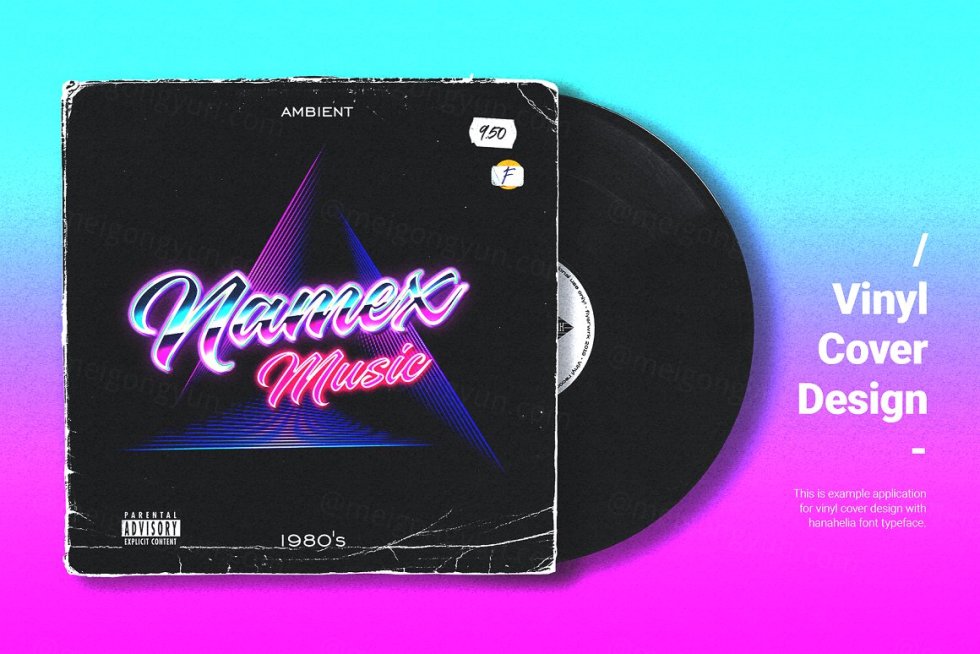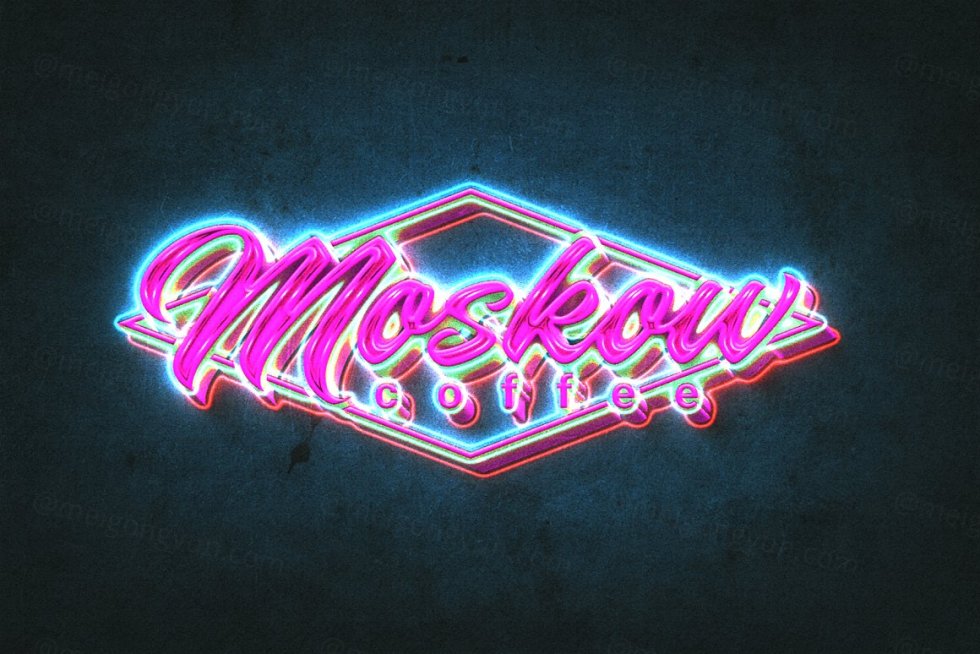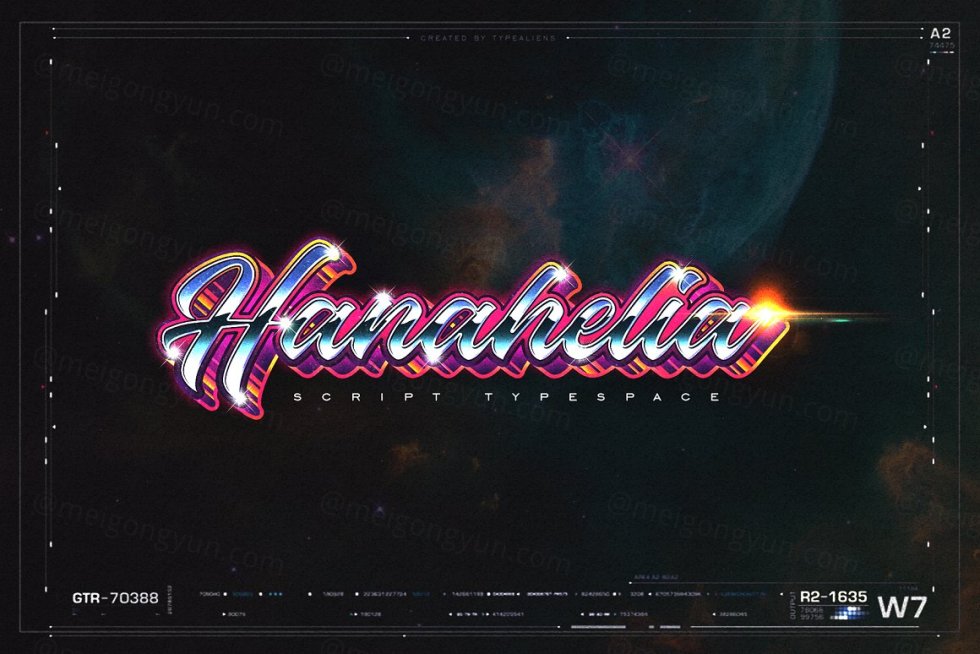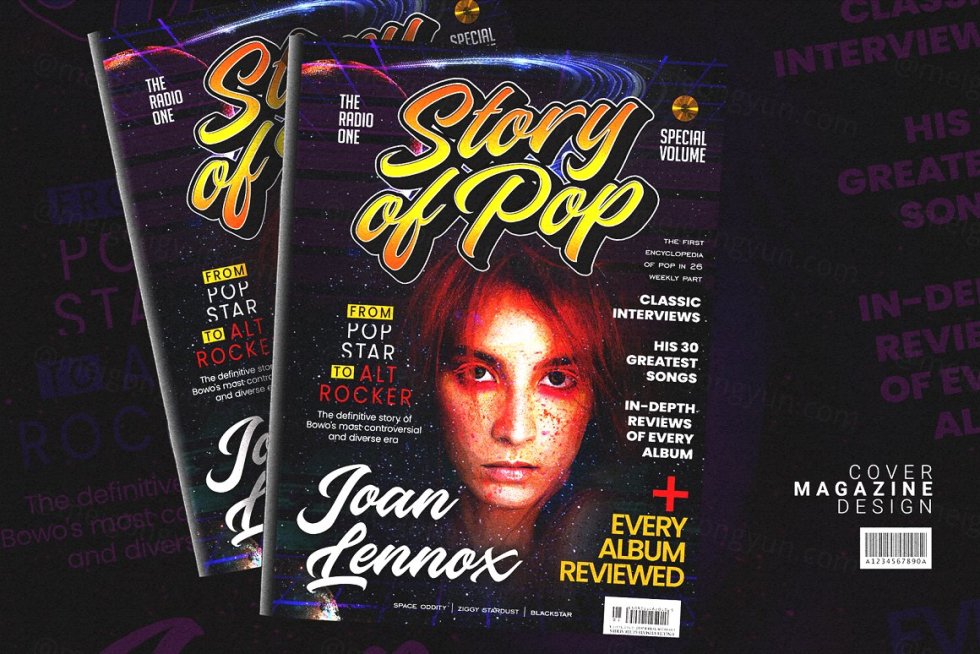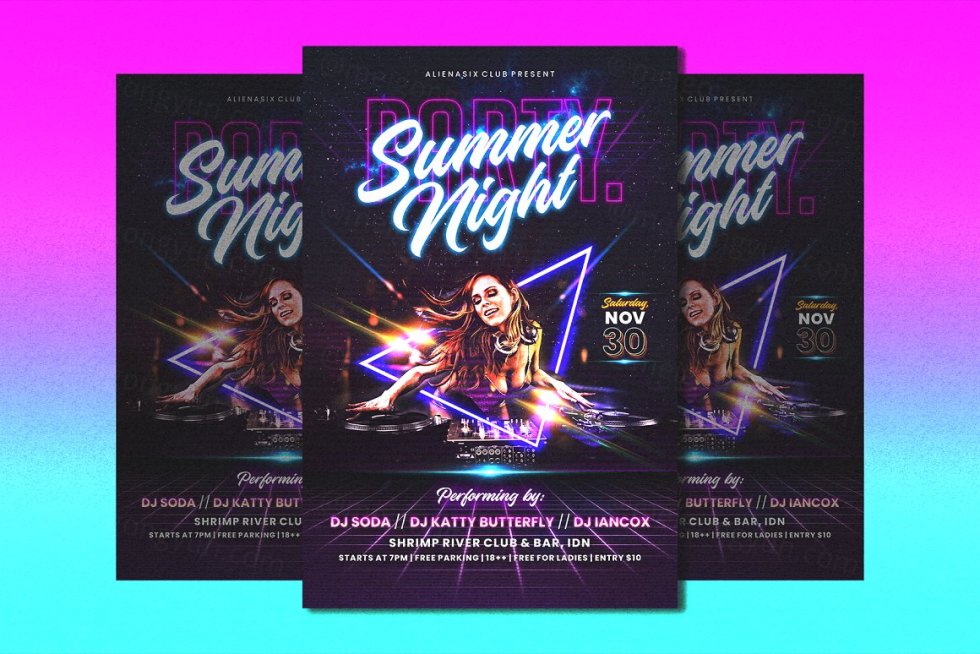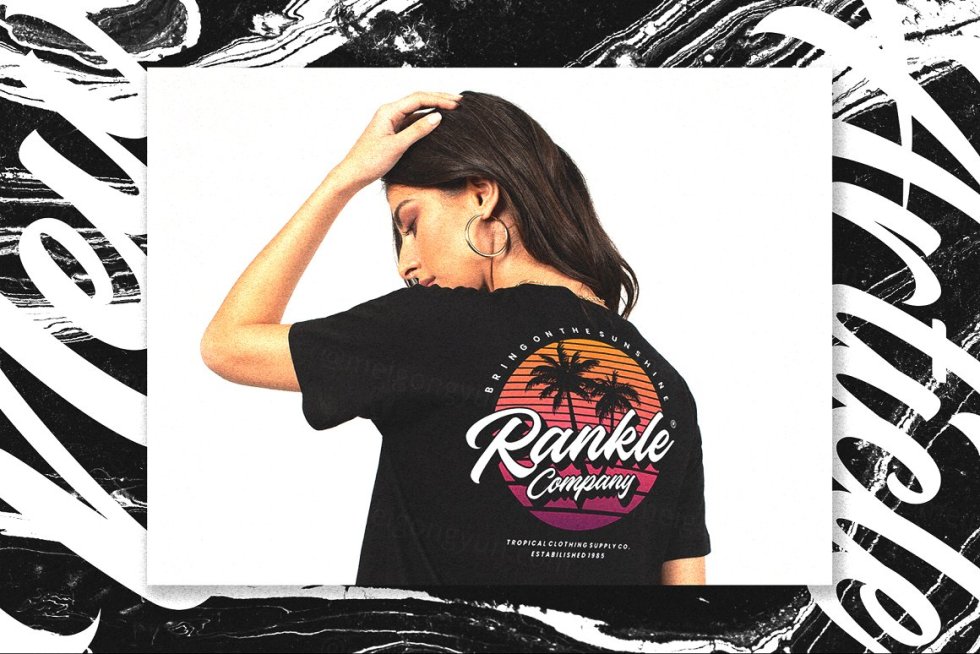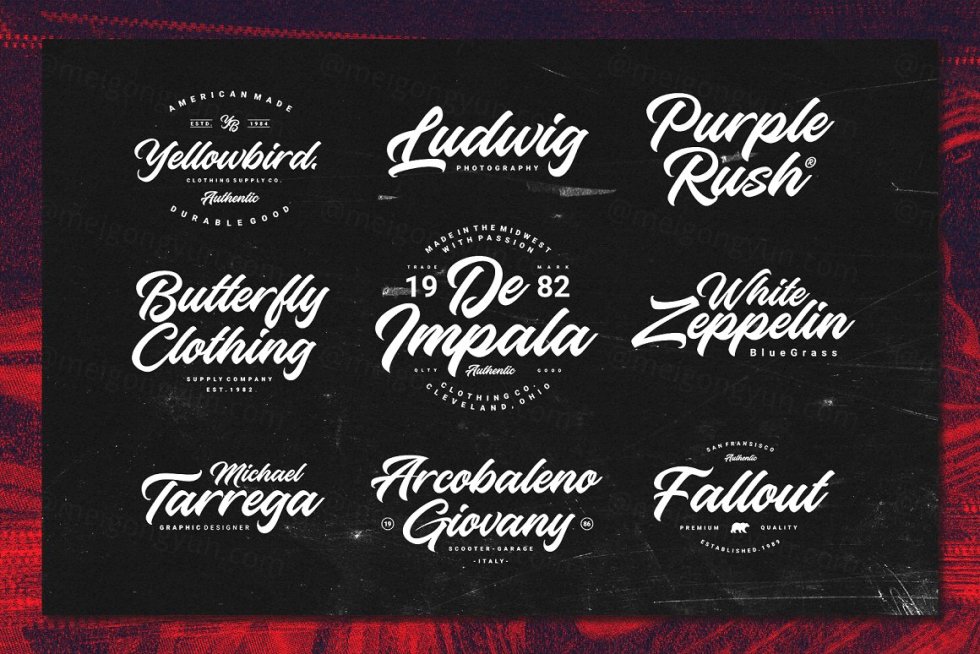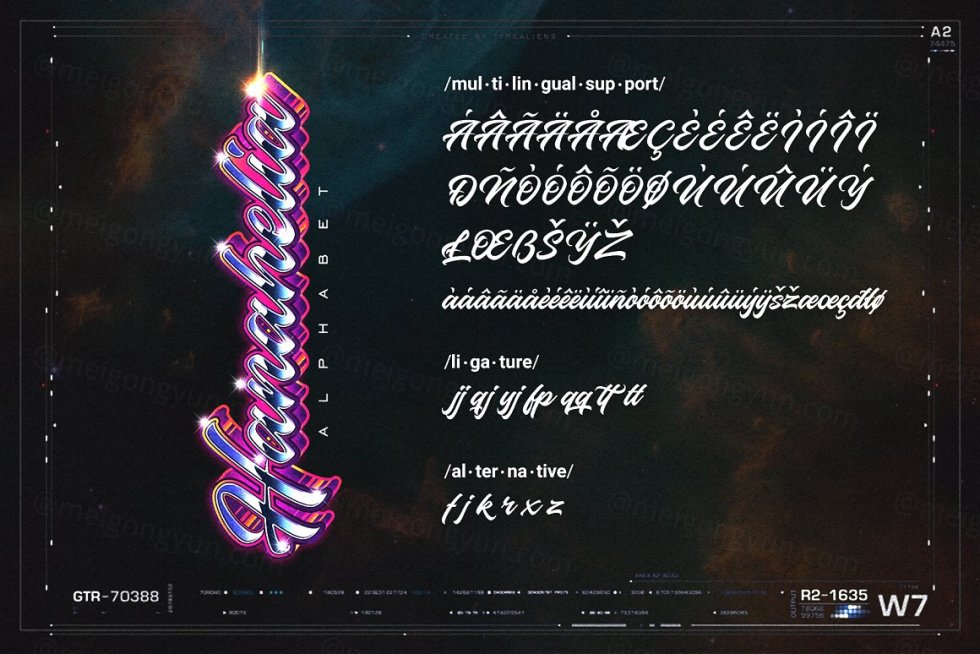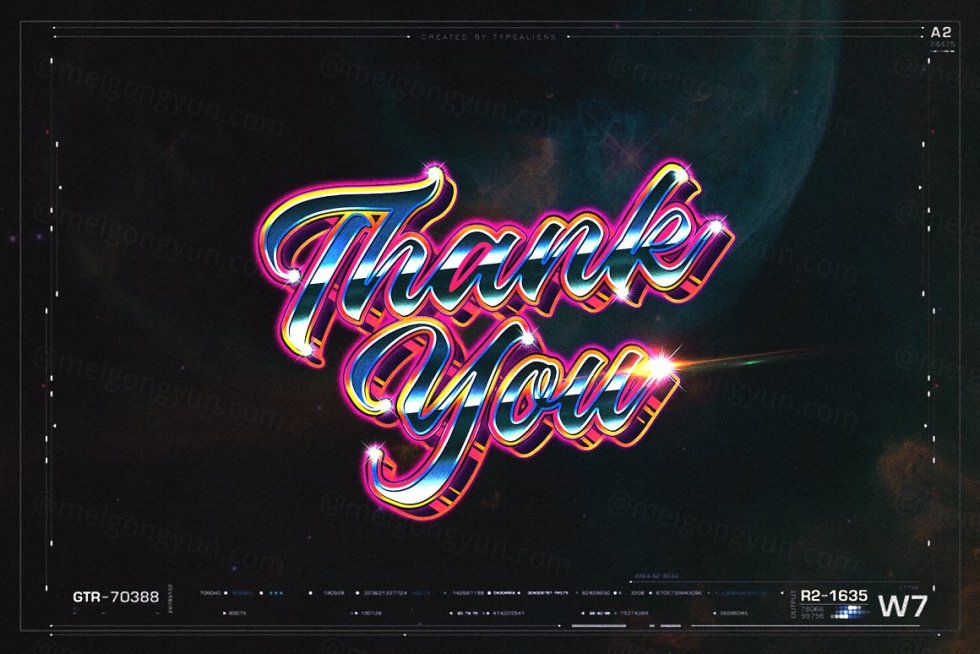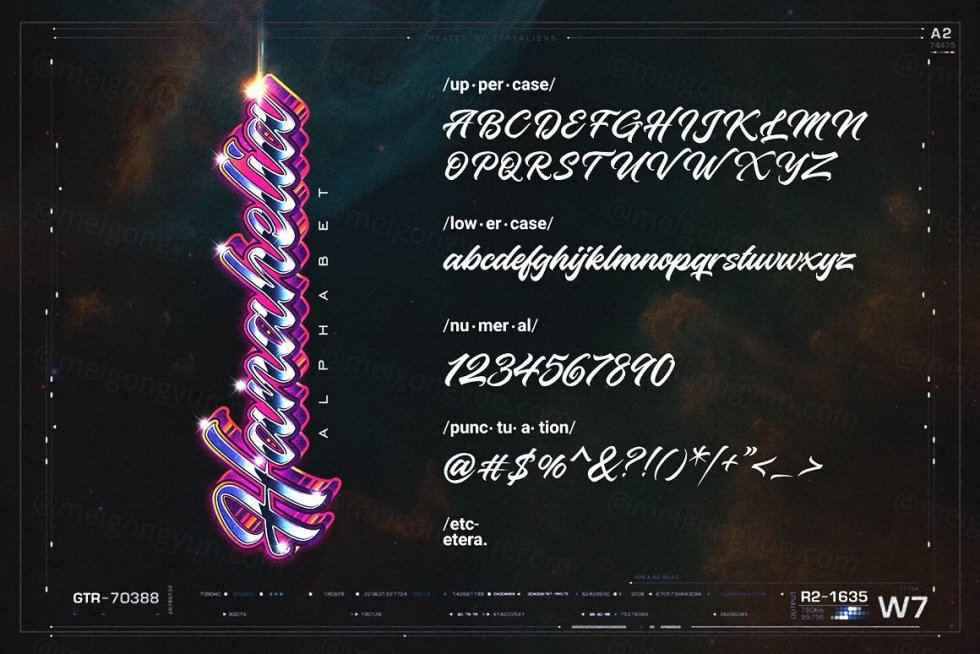
80年代复古霓虹灯海报标识传单广告设计手写英文字体 Ilhamtaro - Hanahelia
Ilhamtaro
手写体
是一种现代脚本,适合在 80 年代显示布局设计。通过添加霓虹灯和闪亮效果,这种字体非常适合设计标识、海报、传单、广告等。
即使它是经典风格,如果您想要干净优雅的现代设计,这种字体也会非常漂亮。